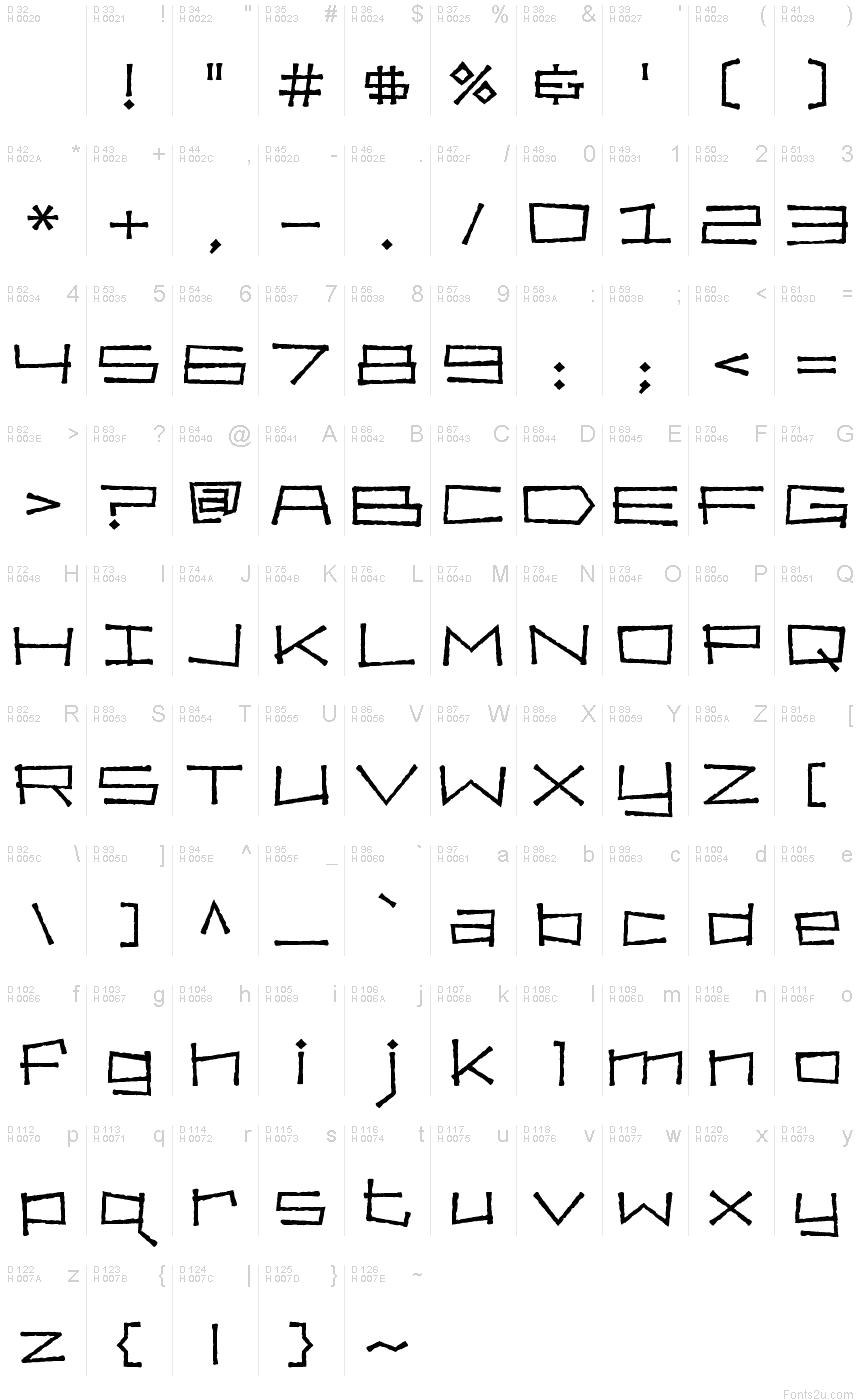
Bahama Slim od Font Diner je bezplatné, záměrně „opotřebované“ display písmo s drsným nádechem ostrovních tabulí. Písmena vypadají jako ručně malovaná a vybledlá od slunce – hranaté tvary, jemně rozechvěné příčné tahy a masivní vertikály dodávají celému fontu uvolněný, ošoupaný a příjemně domácký dojem.
Hodí se na plakáty, branding barů a kaváren, obaly desek, letáky či titulky, kde více než uhlazený styl vynikne právě bezplatné písmo s ležérní, ošoupanou texturou. Díky tomu, že tvary zůstávají jednoduché, zatímco okraje jsou roztřepené, skvěle funguje i v krátkých titulcích a logotypu, které potřebují přímořský, ručně malovaný charakter.
Bahama Slim